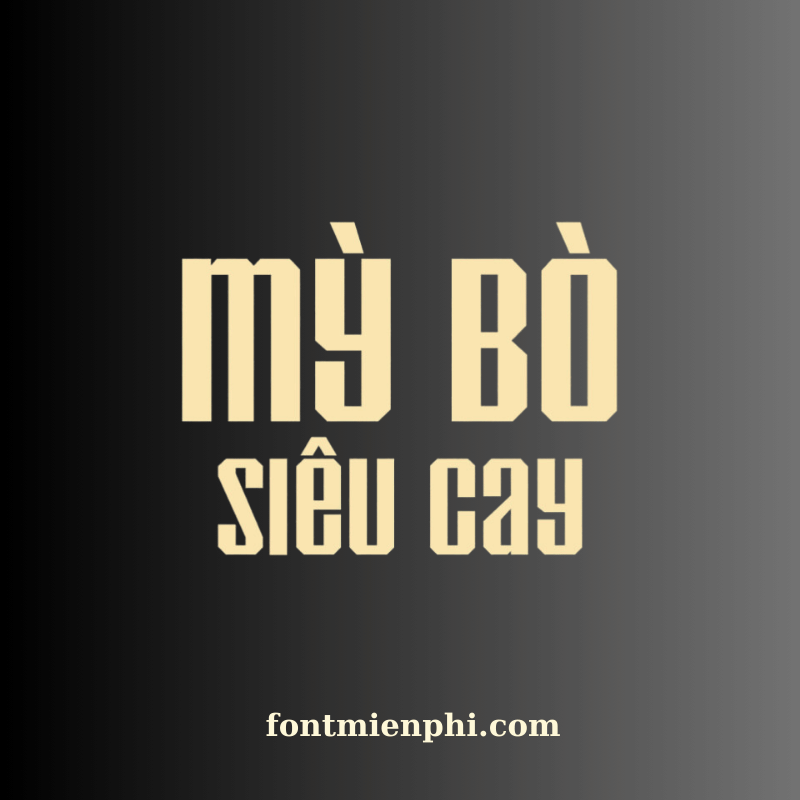
Font Việt hóa 1FTV VIP Inflammable Age  – Phong cách cháy bỏng, đậm chất nghệ thuật
Font Việt hóa 1FTV VIP Inflammable Age là bộ font chữ độc đáo, mang phong cách “cháy bỏng” với nét đậm, sắc sảo và đầy cá tính. Được thiết kế tối ưu cho tiếng Việt, font chữ này phù hợp với các dự án sáng tạo như poster, bìa sách, logo, hoặc các ấn phẩm nghệ thuật cần sự nổi bật. Với đường nét mạnh mẽ và hiệu ứng “lửa cháy”, 1FTV VIP Inflammable Age giúp tạo điểm nhấn ấn tượng trong mọi thiết kế.
✔️ Hỗ trợ đầy đủ tiếng Việt – Đảm bảo hiển thị rõ ràng, không lỗi font.
✔️ Phong cách độc đáo – Nét chữ mạnh mẽ, hiệu ứng cháy sáng tạo.
✔️ Đa dạng ứng dụng – Dùng cho thiết kế đồ họa, quảng cáo, game, nghệ thuật.
Nếu bạn đang tìm kiếm một font chữ Việt hóa ấn tượng, 1FTV VIP Inflammable Age là lựa chọn hoàn hảo để thể hiện phong cách mạnh mẽ và sáng tạo. Tải ngay để khám phá khả năng ứng dụng tuyệt vời của font chữ này trong các dự án thiết kế của bạn!